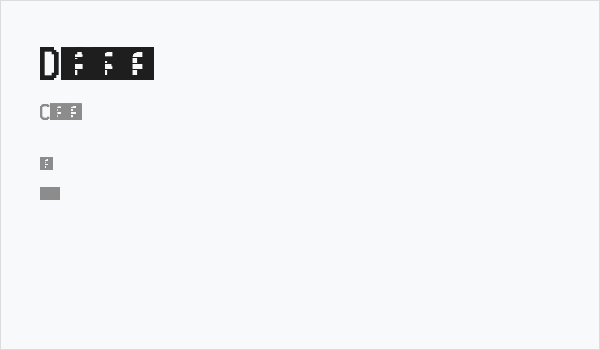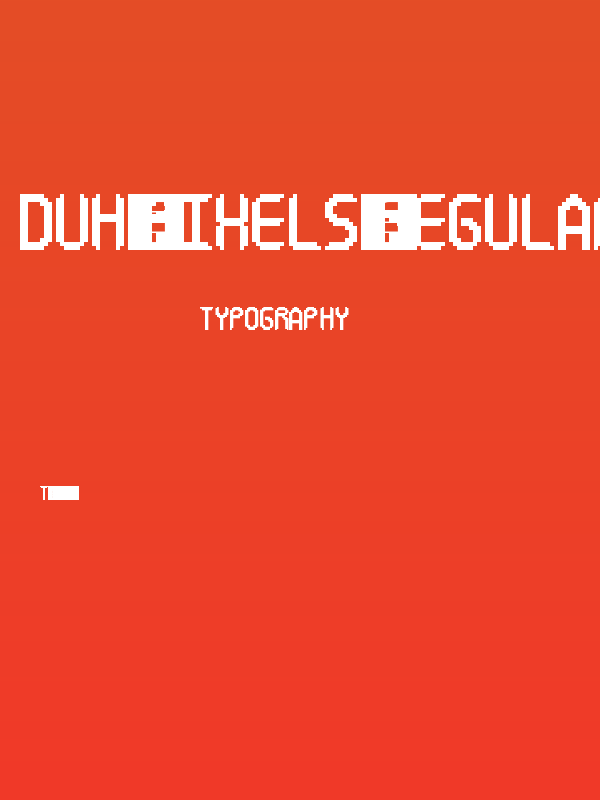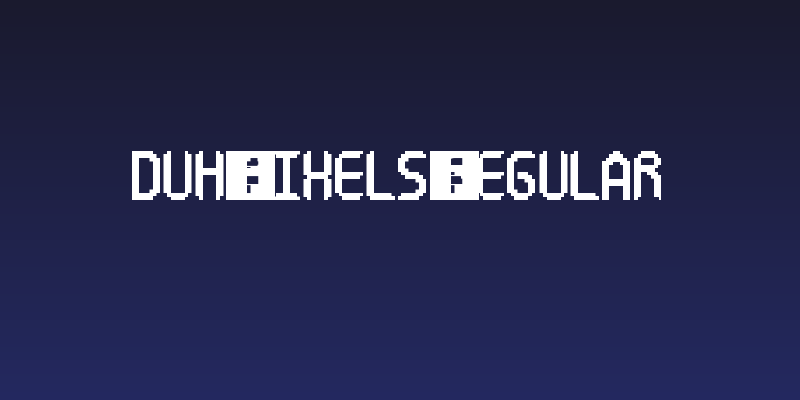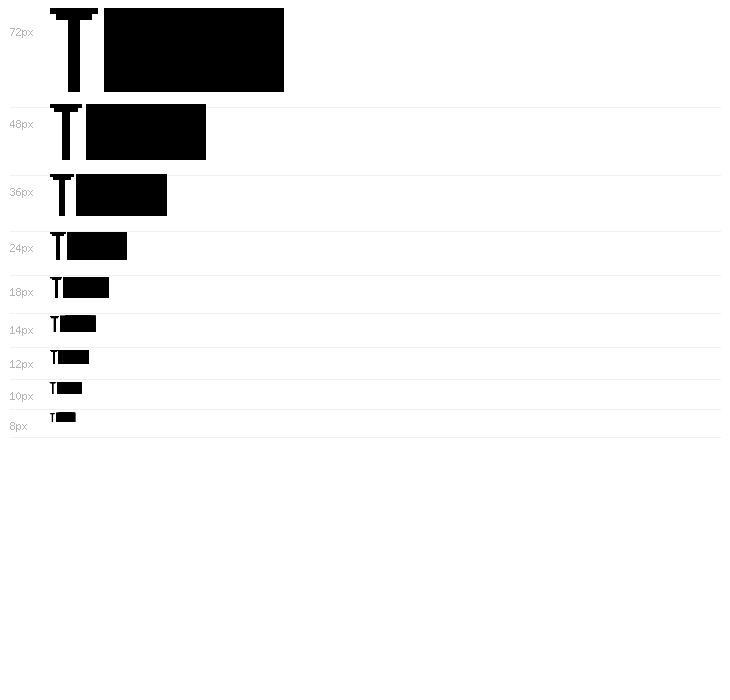
Duh, Pixels! Regular Font
✎ Pixel
| Gesamtstil | Retro, Digital |
| Anwendungsfall | Headlines, Logos, Digital displays |
| Vorgeschlagene Projekte | Perfect for video game graphics, retro-themed posters, digital art, and tech-related branding. |